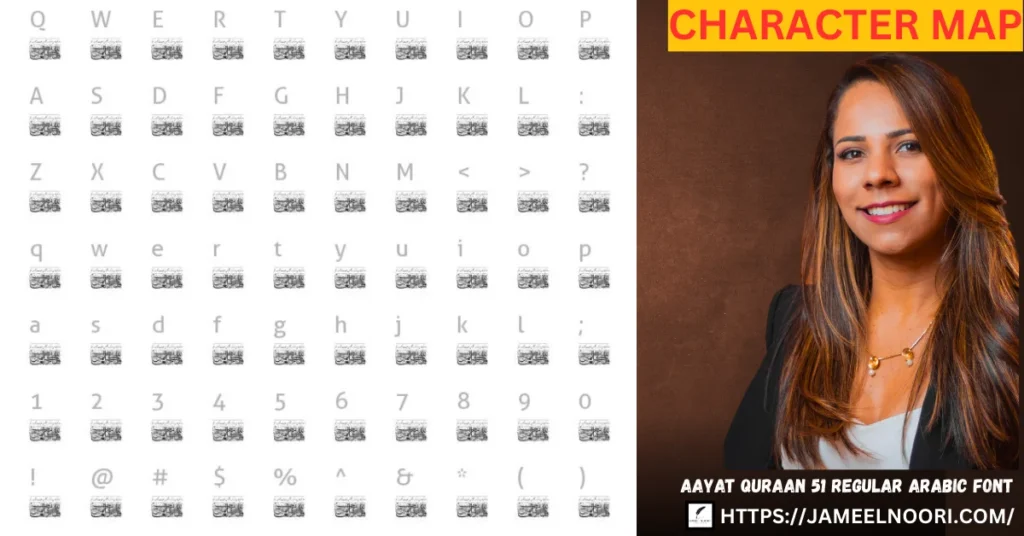
What is Aayat Quraan 51 Regular Arabic Font?
Aayat Quraan 51 Regular Arabic Font ek beautifully designed Arabic font hai jo Quranic aur Arabic text ki calligraphy ke liye perfect hai. Ye font high readability aur professional look ke liye famous hai. Pakistan ke users is font ko websites, blogs aur digital documents me use karte hain.
Calligraphy and Character Map of Aayat Quraan 51 Regular True Type Arabic Font
Aayat Quraan 51 Regular Arabic Font ki unique calligraphy isay Arabic aur Urdu content ke liye ideal banati hai. Character map section me aap har letter aur diacritical mark ka detailed view dekh sakte hain.
Best Use Cases of Aayat Quraan 51 Regular Arabic Font
Aayat Quraan 51 Regular Arabic Font ka use har digital aur print project me kiya ja sakta hai. Kuch popular use cases:
- Islamic websites aur blogs
- Quranic apps aur eBooks
- Arabic and Urdu headings for publications
- Graphic design aur social media posts
Ye font best Arabic font ke category me aata hai aur Pakistan me widely preferred hai.
Aayat Quraan 51 Regular Arabic Font ek high-quality, professional TrueType font hai jo Urdu aur Arabic content ke liye best choice hai. Is font ki clean calligraphy aur easy readability isay blogs, websites, social media posts, aur digital documents ke liye ideal banati hai. Pakistan me ye font widely used hai aur beginners aur professionals dono ke liye perfect hai. Agar aap Quranic ya Arabic content me attractive aur readable text chahte hain, to Aayat Quraan 51 Regular Arabic Font ka use aapke projects ko next level tak le ja sakta hai.
It is a Regular TrueType font widely used for Arabic and Urdu text, especially for Quranic content.
Yes, its clean calligraphy makes it ideal for professional use.
Absolutely, it is perfect for websites, apps, and social media posts.